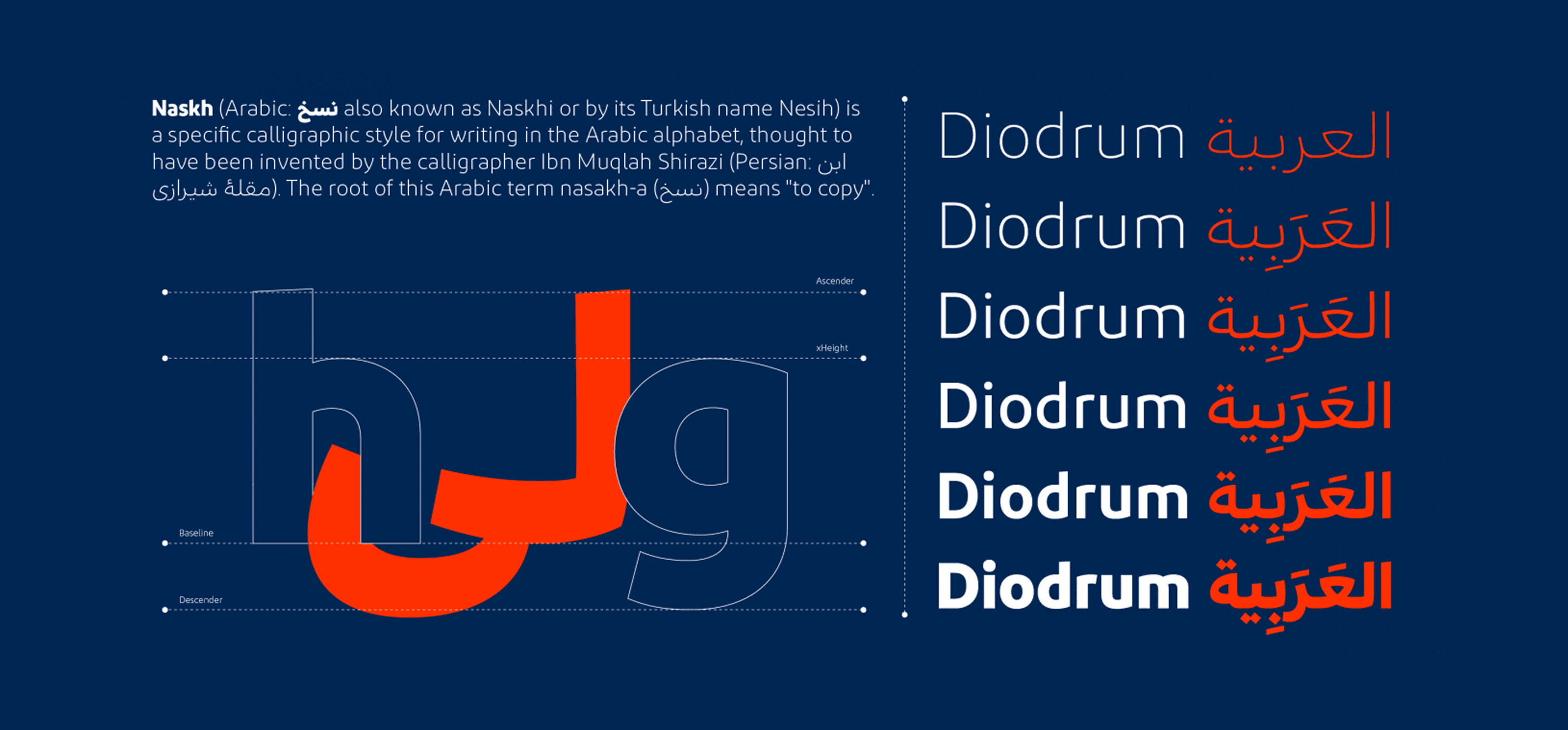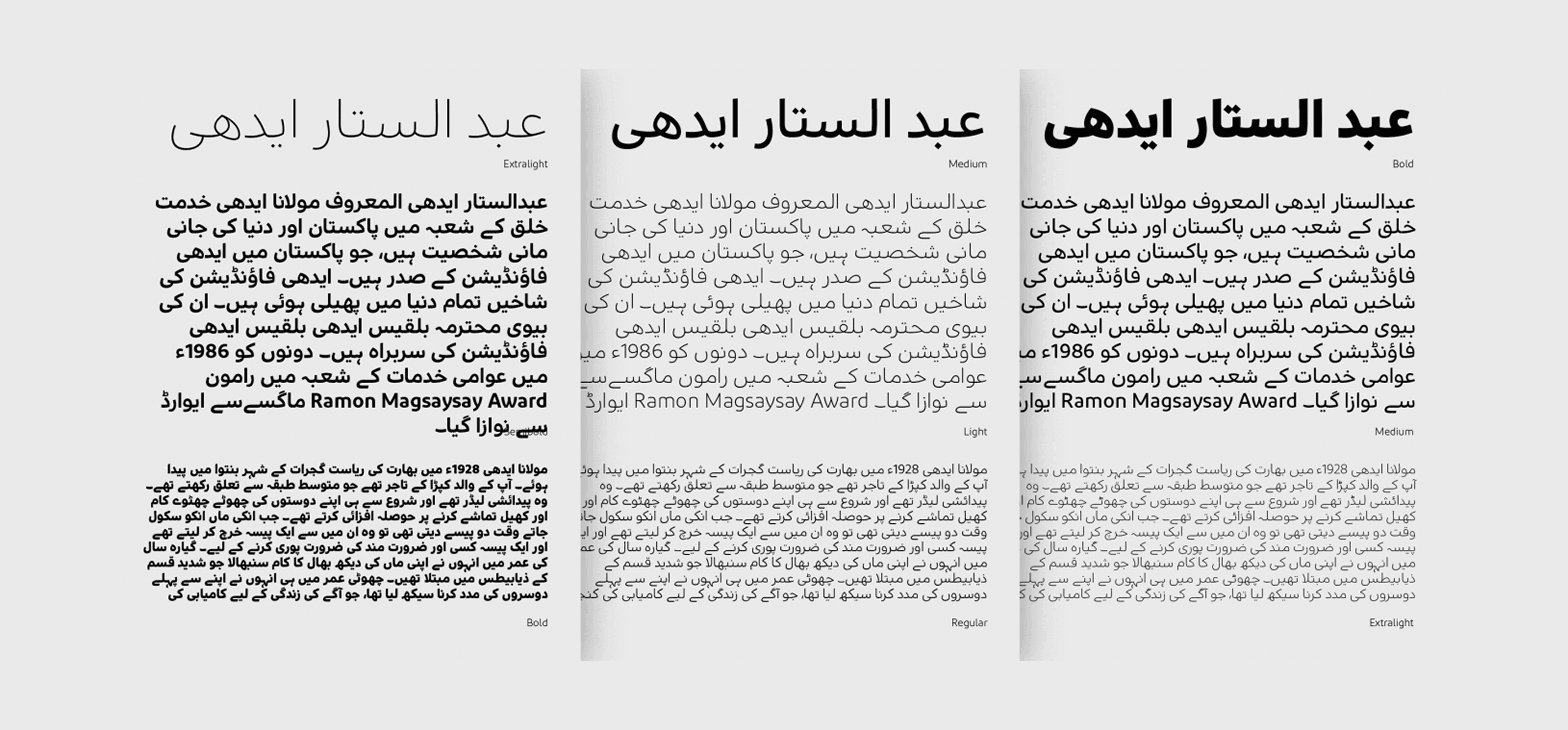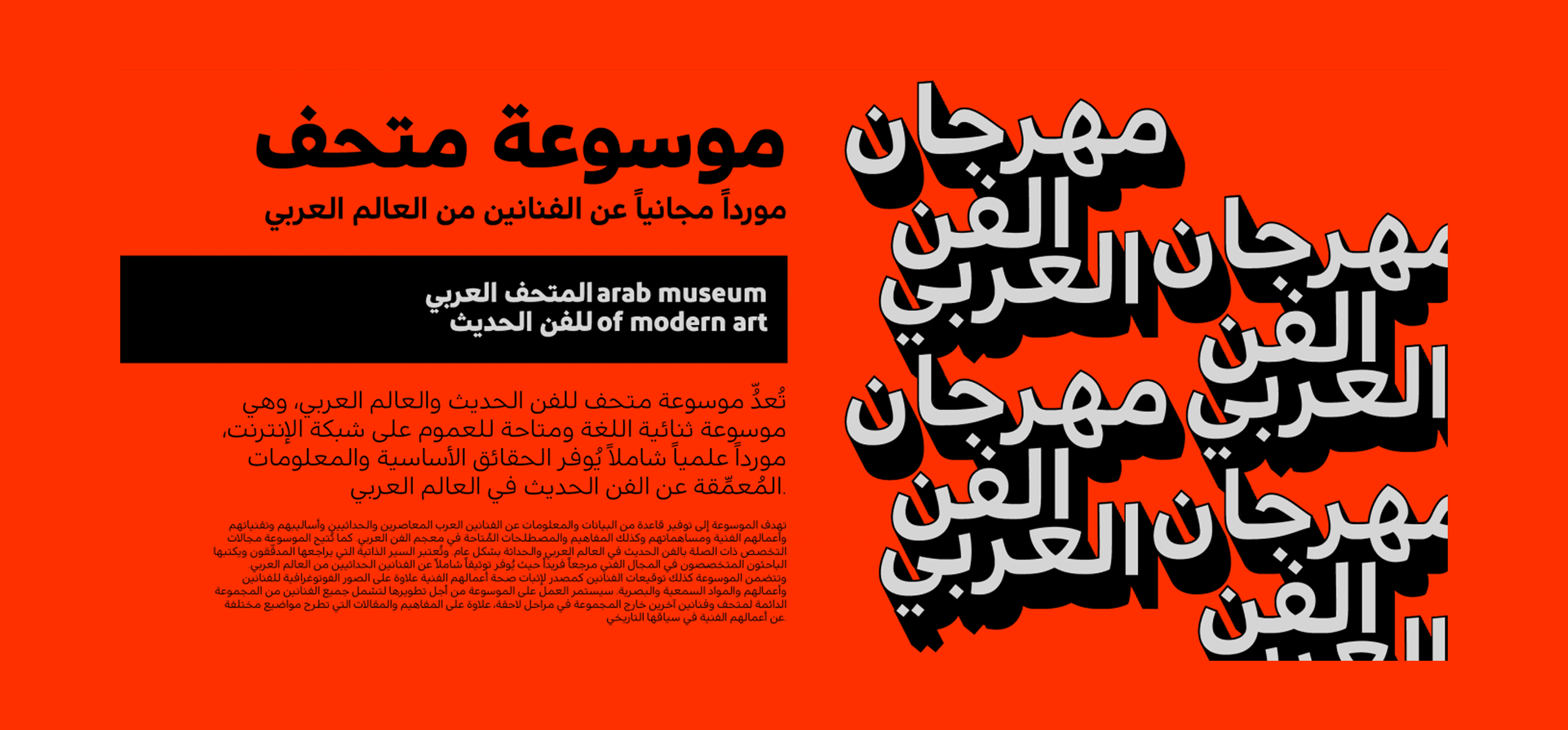
خط Diodrum Arabic هو خط نسخ منخفض التباين يتكون من ستة أوزان، وقد تم تحسينه ليكون مناسبًا لأعمال الهوية البصرية للشركات، وتصميم التحرير (Editorial Design)، ومشاريع واجهات المستخدم UI/UX.
الخط يأخذ بعين الاعتبار الطابع الأفقي الغالب في النصوص العربية مقارنة باللاتينية. ونظرًا لأن تصميم الحروف العربية واللاتينية في Diodrum يتميز بتساوي السُمك (monolinear)، تم استخدام وسيلة أخرى لإبراز الأفقية: حيث تأتي المساحات الداخلية للحروف (Counterforms) كبيرة ومفتوحة، كما تم التأكيد على الأجزاء الوسطى من الحروف.
تبدأ أو تنتهي العديد من ضربات الحروف بخطوط مائلة قليلاً، ما يضفي لمسة خفيفة من الطابع الكلاسيكي المستوحى من الخط العربي التقليدي داخل الشكل الحديث للخطوط الهندسية، وينطبق هذا أيضًا على النقاط والعلامات في الحروف العربية ضمن هذا الخط.